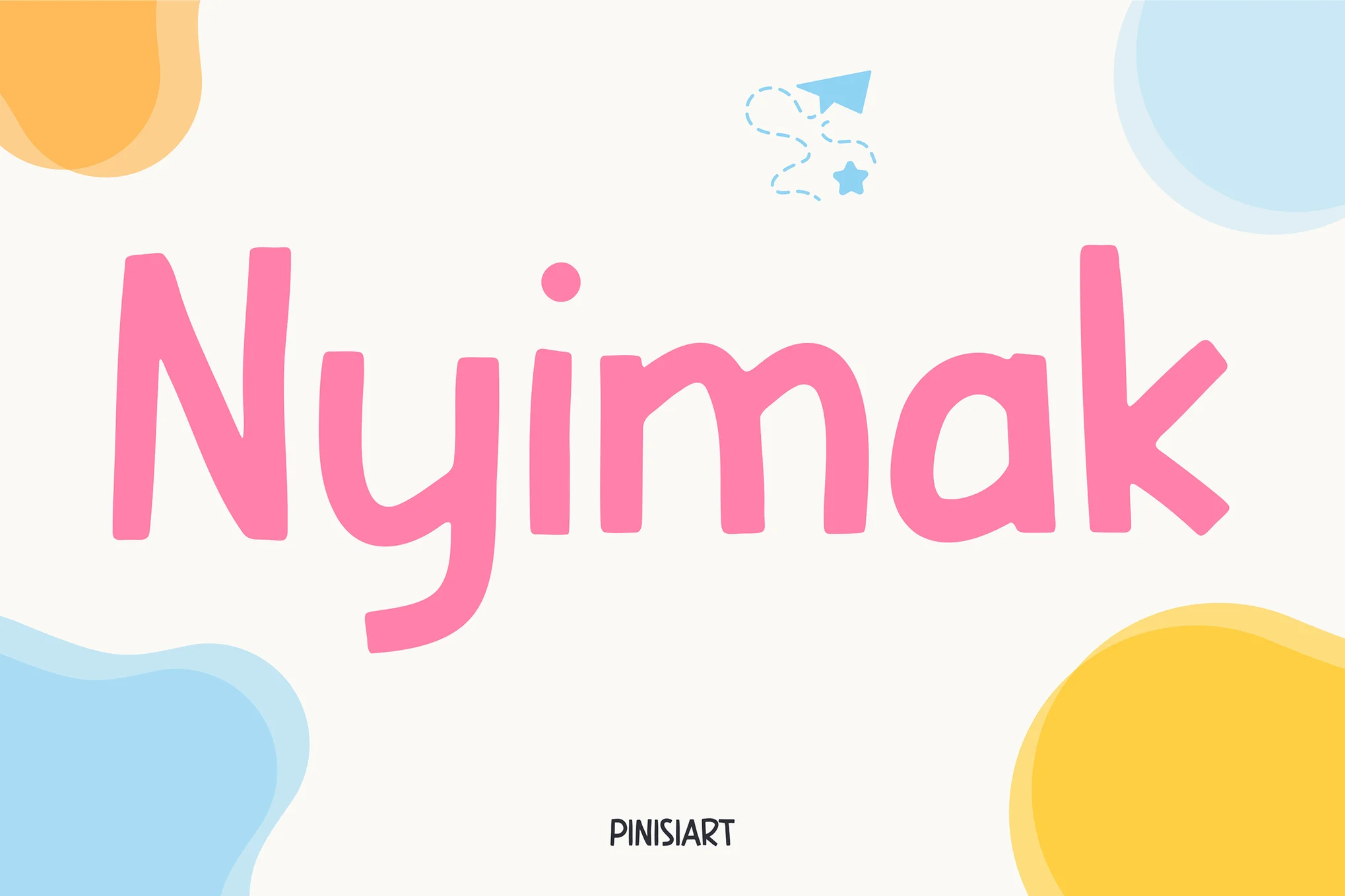
✨ فونت آموزشی Nyimak – طراحی کودکمحور با حس دوستانه و امن
Nyimak یک فونت دستنویس با ساختار سنسریف و گوشههای گرد است که بهطور خاص برای کودکان، معلمان و محیطهای آموزشی طراحی شده است. این فونت با ترکیب لطافت و خوانایی بالا، گزینهای ایدهآل برای کتابهای کودکان، پوسترهای کلاس، برنامههای آموزشی، کاربرگها و برندینگ مدارس بهشمار میرود.
🎨 چرا فونت Nyimak؟
- دارای فرمهای گرد و ملایم که حس امنیت و راحتی بصری را منتقل میکند
- دستنویس اما ساختارمند – ترکیبی از بازیگوشی و وضوح آموزشی
- طراحیشده با تمرکز بر قابلخواندن بودن برای کودکان نوآموز
- مناسب برای چاپ و صفحات دیجیتال با حفظ کیفیت در تمام سایزها
- الهامگرفته از فرمهای طبیعی نوشتار کودکانه با نظم کافی برای آموزش
📚 موارد استفاده:
- کتابهای داستان و آموزشی کودک
- پوسترها و تابلوهای کلاس درس
- فلشکارتها و تمرینهای درسی
- اپلیکیشنهای یادگیری و بازیهای آموزشی
- برندینگ و لوگوی مدارس، مهدکودکها و مراکز رشد
💡 ویژگیهای فونت:
- سبک سنسریف با لبههای گرد و دلنشین
- مجموعه کامل حروف بزرگ و کوچک، اعداد و علائم نگارشی
- محبوب برای طراحیهای آموزشی، کودکانه و خلاقانه
Nyimak یادگیری را به بازی تبدیل میکند. اگر به دنبال فونتی هستید که حس دوستانه، شاد و آموزنده داشته باشد، Nyimak گزینهای بیرقیب برای پروژههای کودکمحور شماست.